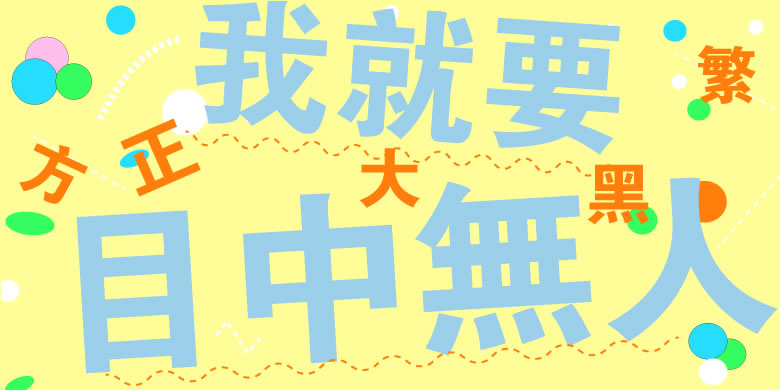
方正大黑
方正大黑,这款字体结构工整、笔画清晰,兼顾美观与易读性,适用于标题、正文、海报、包装、LOGO 等多种场景。字形优雅稳定,风格百搭耐看,适配日常排版与创意设计,让文字呈现更舒适、更具质感。方正大黑一笔一画,皆是细节,以均衡的比例、流畅的线条打造舒适视觉体验,字形端正大气,风格简约现代。无论是商业设计、品牌宣传还是日常排版,都能轻松驾驭,让文字更有格调与力量。方正大黑字体下载。
方正大黑源自1971年上海字模一厂设计的行头黑,字形结构延续了铅字时代的黑体风格。这款字体的中宫紧凑,横竖笔画的两端没有喇叭口,竖和撇的起笔留有细微的饰角,笔画粗壮有力。方正大黑的整体风格中庸平和,具有明显的时代特征,适用于报刊、杂志和书籍中的大型标题。